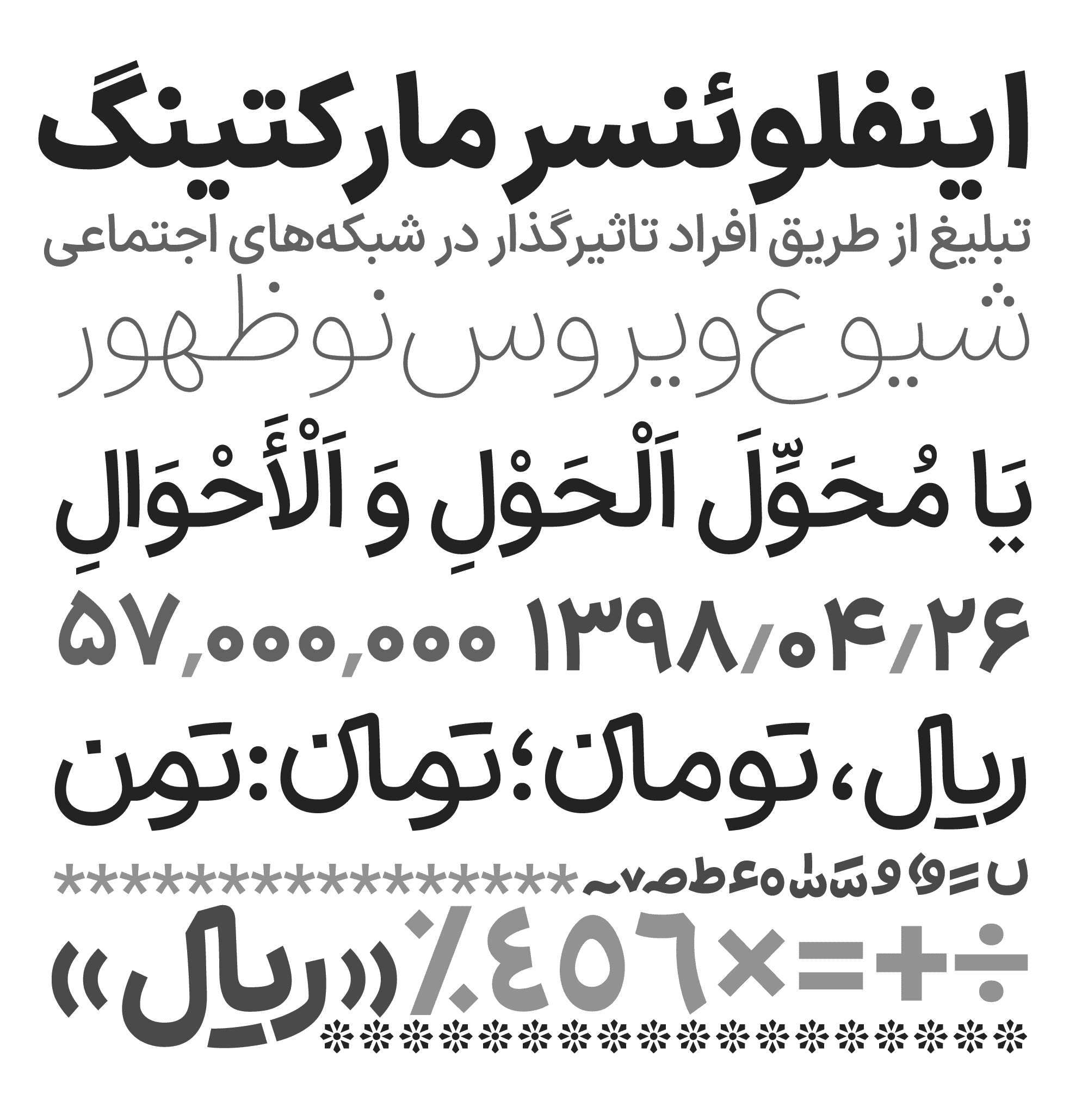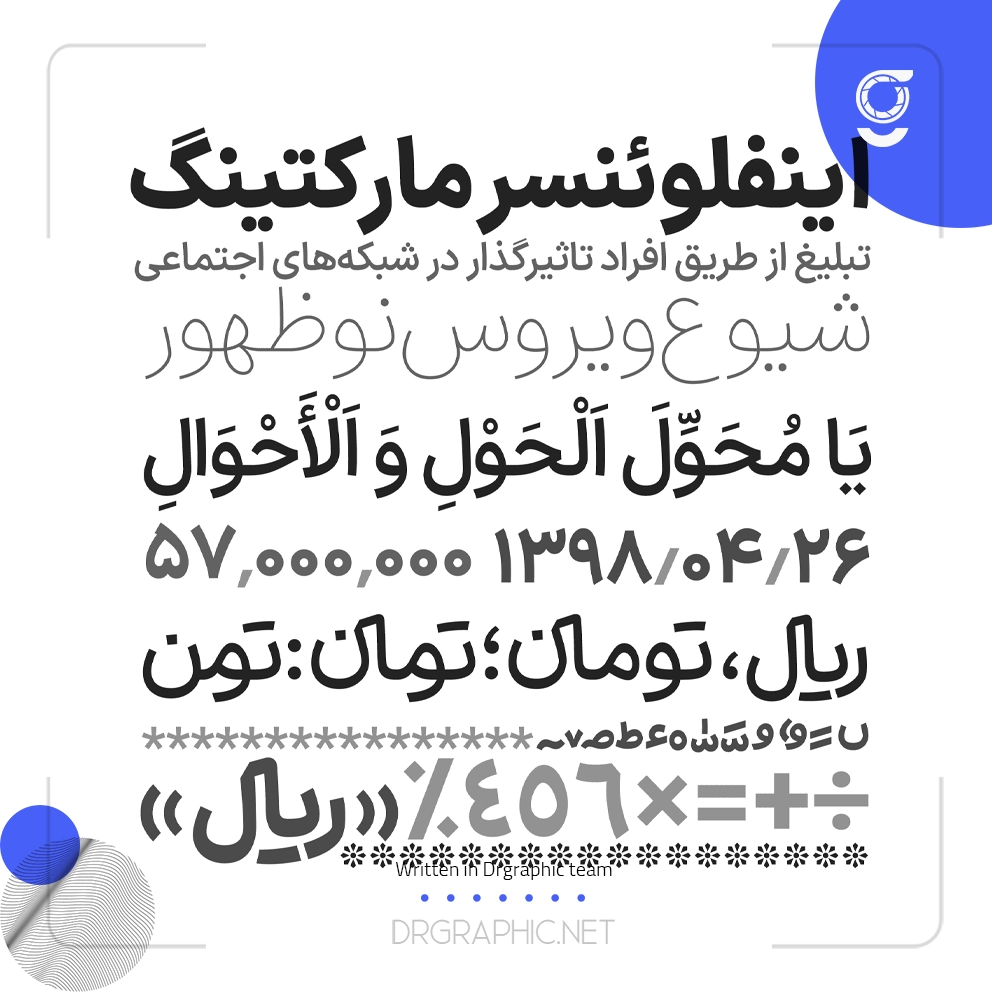
فونت ایران سنس پرطرفدارترین فونت فارسی در سالهای اخیر بوده است. با دکترگرافیک همراه باشید.
اسنپ، دیوار، آپارات و صدها وب سایت و اپلیکیشن برتر ایرانی از ایران سنس استفاده میکنند.